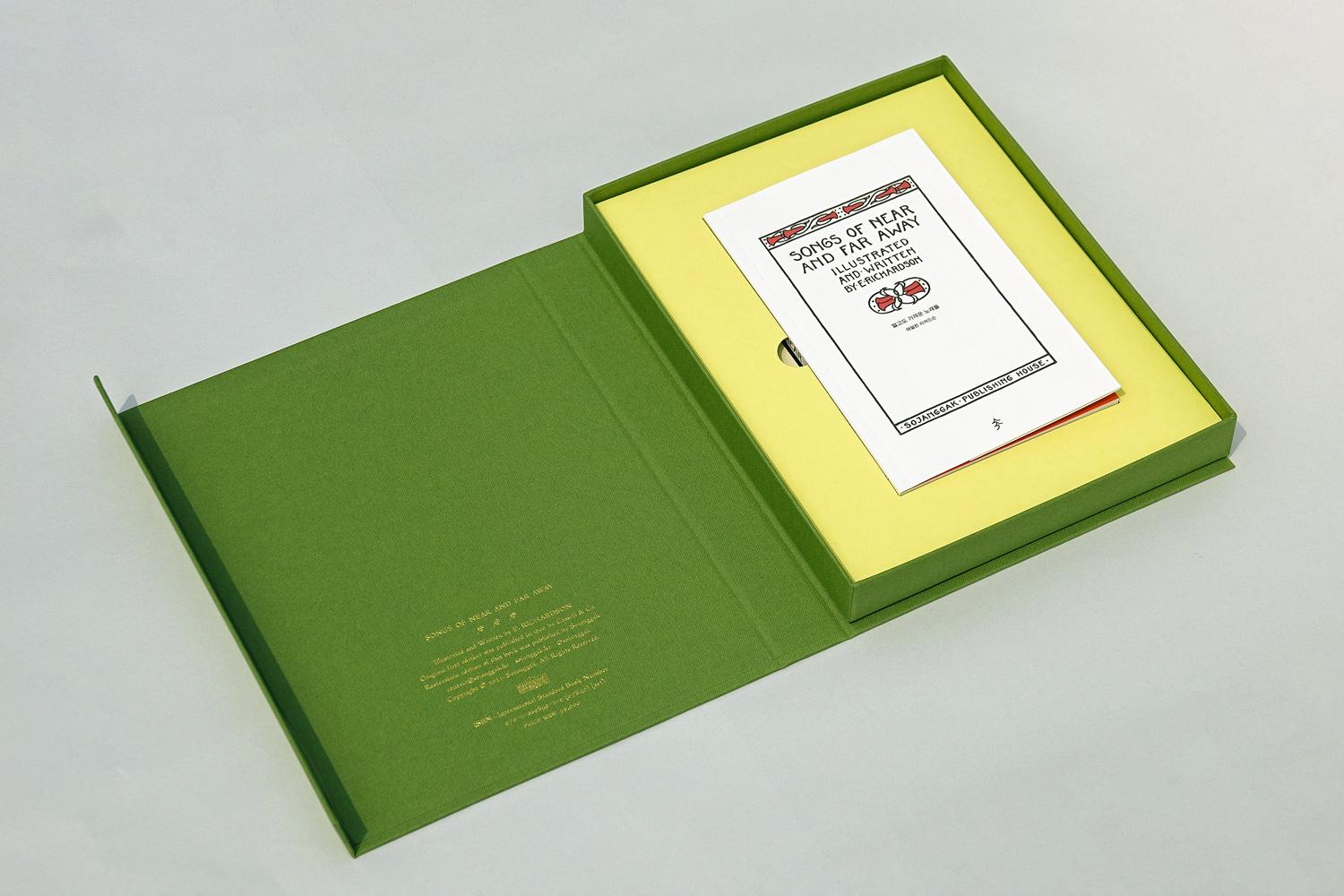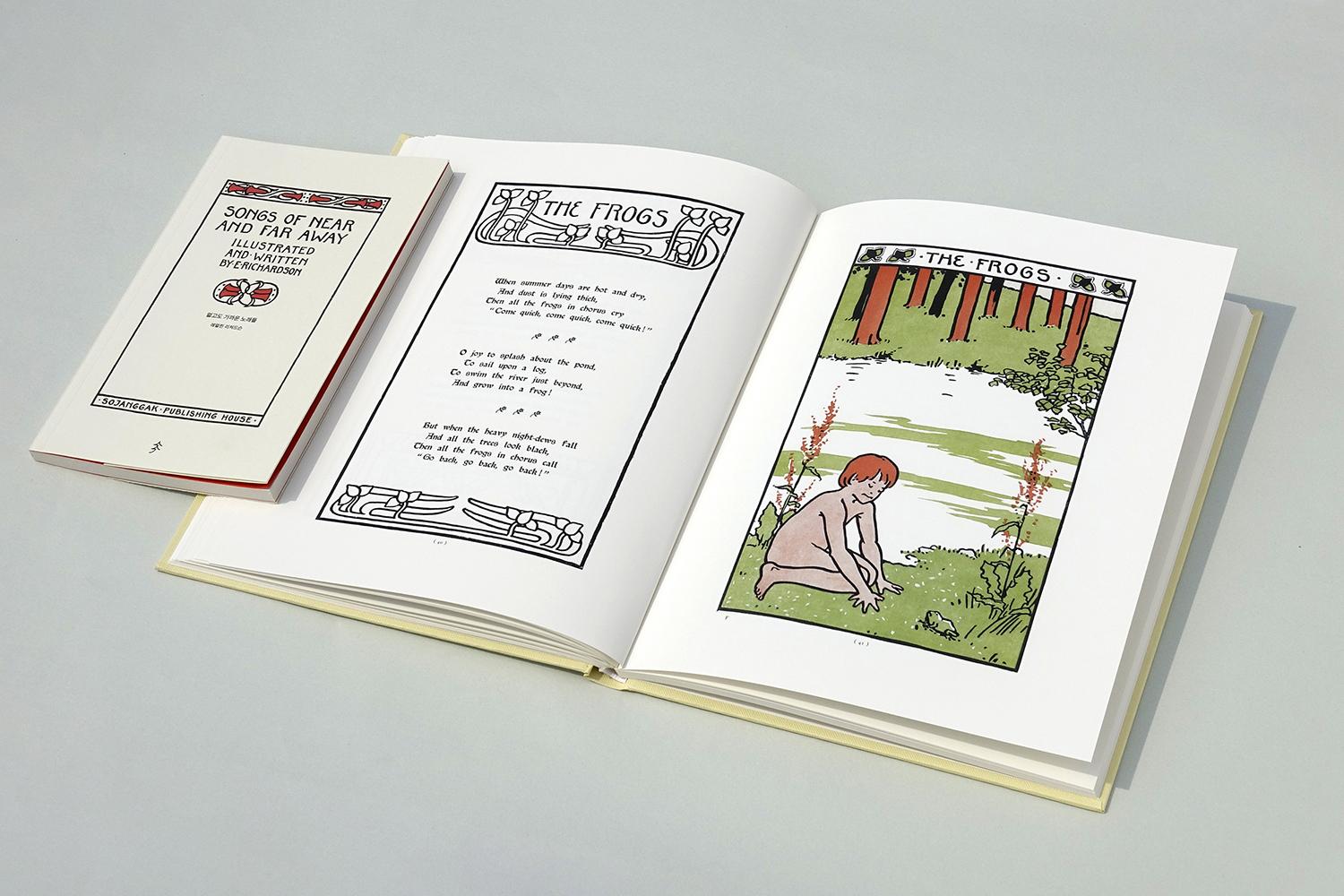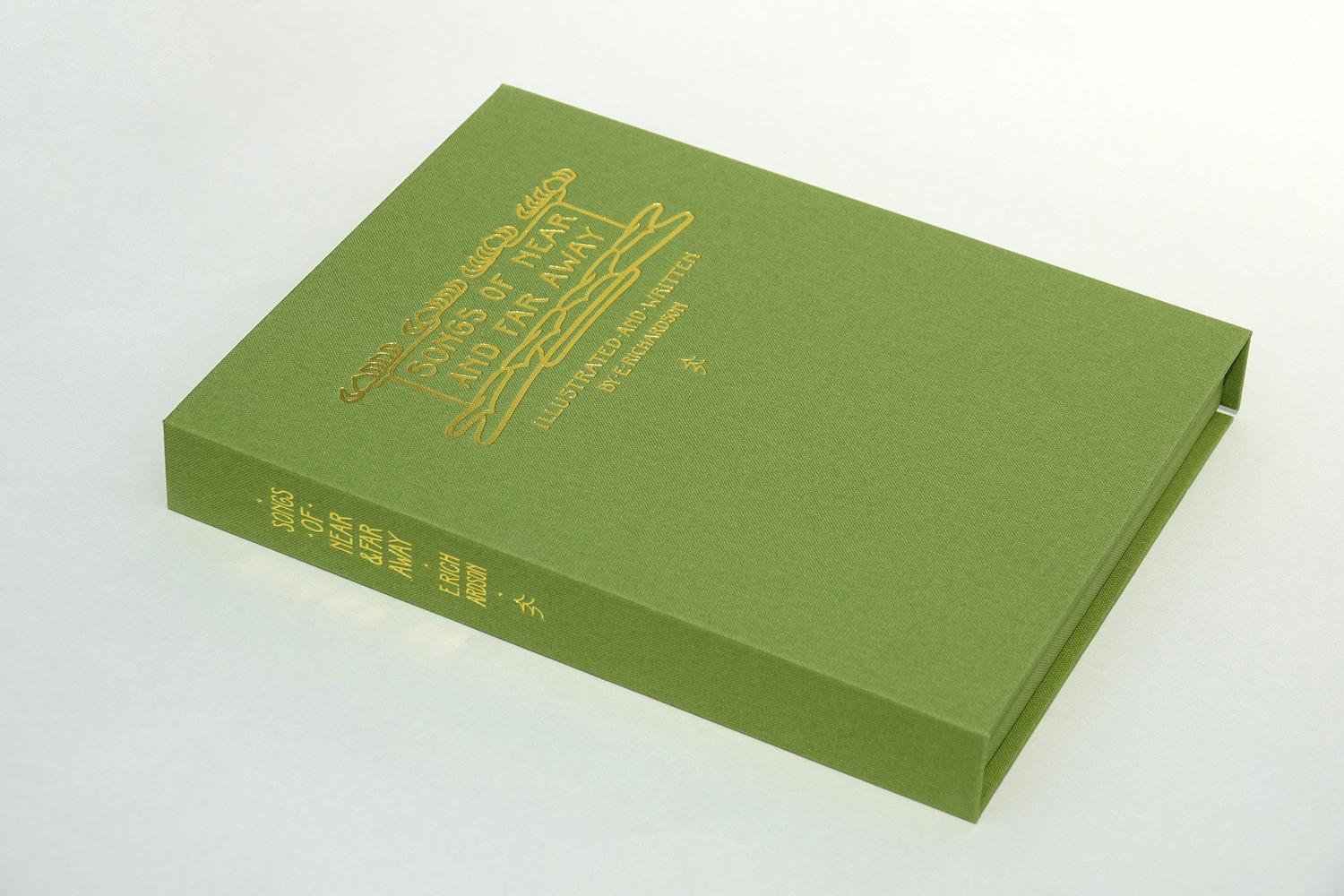
인터뷰: 소장각의 소장, 노성일 디자이너
소장각은 동남아시아를 중심으로
다양한 문화권의 이야기를 발굴해 그 가치와 매력을 독자에게 전합니다.
노성일 디자이너는 지역과 시대의 맥락을 존중하며,
현지인의 시선과 목소리를 온전히 담는 방식을 고집합니다.
캄보디아의 크메르 문자, 태국의 문방구, 미얀마의 달력까지,
동남아시아 곳곳의 이야기를 발견하고 다듬어 한 권의 아름다운 책으로 완성합니다.
책 속의 폰트 하나, 색감 하나까지도 맥락에 맞춰 치밀하게 선택하는
그의 집요하고 섬세한 디자인 방법론과 사용 폰트들을 살펴보세요.
Intro:
작은 책들의 집, 소장각
―독자분들을 위해 소장각의 간단한 소개를 부탁드립니다.
안녕하세요, 소장각의 노성일 소장입니다. 소장각은 ‘작은 책들의 집’이란 뜻의 출판사이자 디자인 스튜디오로, ‘주변부’, ‘독창성’, ‘아름다운 형태’ 세 가지 키워드를 중심에 두고 책을 만들어요. ‘주변부’라고 하면 흔히 원의 바깥을 떠올리시는데, 제가 말하는 건 그 개념보다는 바로 옆에 있는 친구나 이웃을 바라보는 시선, 그들의 이야기에 귀 기울이는 걸 말합니다. 사람들과 대화를 나누다 보면 눈이 반짝반짝 빛나는 순간들을 발견하게 되는데, 그게 바로 그 사람이 가진 독창성이라고 생각해요. 저는 그걸 건져 올려서 아름다운 형태로 엮는 일을 하고 있습니다.
―소장각이라는 이름은 어떻게 짓게 되셨나요?
‘규장각’에서 따와 ‘작은 책들의 집’이라는 의미로 지었습니다. ‘소장각'이라는 유행어를 의식해서 지은건 아니고요. 여기서 ‘작은 책’이란 유명하거나 주목받는 책이 아닌, 주목받지 않더라도 가치 있는 책을 말합니다. 또 이름에 한자*(小章閣)를 쓴 건, 아시아인으로서의 정체성을 생각할 때 한자 문화권의 역사와 의미가 중요하다고 느꼈기 때문이에요. 요즘은 한국에서 한자 쓰는게 많이 없어진 것 같고, 서양의 방식을 차용한 네이밍이 트렌드죠. 저는 그와는 다른 방향이 필요하다는 생각이 들었습니다.
*小[작을 소]‧章[글 장]‧閣[집 각]
집 모양의 한자 로고와 숲과 나무를 표현한 한글 로고
―한글 자소를 세로로 쌓은 형태의 로고, 한자로 구성된 로고도 매우 감각적인데요.
로고는 제가 직접 만들었고, 한자로 구성한 로고와 한글 자소 ‘ㅅ·ㅈ·ㄱ’ 으로 만든 로고 두 가지를 함께 쓰고 있어요. 한자가 *표의문자니까, 이미지처럼 보이길 바라는 마음에 집 모양으로 만들었습니다. 閣[집 각]의 문 아래 ‘各'이 사실 두 번 들어가 있는데, 손을 맞잡고 있는 두 사람처럼 보이지 않나요? 책은 여러 사람이 같이 공유하고 얘기를 나눌 때 더 풍성해진다는 의미를 담았습니다. 한글 로고는 책 등에 넣을 만한 작은 크기에서 보다 단순하고 선명한 로고가 필요하다고 생각해서 만들게 되었어요.
*표의문자: 하나하나의 글자가 언어의 음과 상관없이 일정한 뜻을 나타내는 문자. 고대의 회화 문자나 상형 문자가 발달한 것으로 한자가 대표적이다.
―'발굴'과 ‘덕질’이라는 키워드도 소개글에 자주 쓰시는데, 특별히 좋아하시는 이유가 있을까요?
저는 ‘발굴’과 ‘덕질’을 비슷한 개념으로 봅니다. 사람들이 눈을 반짝이며 이야기하는 건, 대개 오랫동안 관심을 가져왔고 계속 생각해 온 주제이거든요. 그건 그 사람의 ‘덕질’이고, 저는 그걸 찾아내는 ‘발굴’을 하는 거죠. 그 이야기들이 사소할 수도 있고, 상업적으로는 팔리기 어려울 수도 있어요. 하지만 저는 그 시간과 삶이 가진 가치를 디자이너의 시선으로 보고, 오랫동안 쌓인 것들을 아름답게 포장해 소개하는 게 중요하다고 생각합니다.
소장각의 책
⟪크메르 문자 기행⟫ 표지
―⟪크메르 문자 기행⟫은 대학원 논문으로 시작된 작업으로 알고 있는데요. 캄보디아 문자를 다루게 된 계기가 있었나요?
처음 시작은 예전부터 가고 싶었던 앙코르 와트를 보자는 마음으로 캄보디아로 떠난 거였는데요. 천 년 전의 고대 문자가 여전히 쓰이고 있고, 시간이 흐르며 전혀 다른 형태로 발전해 온 과정을 발견하게 되었어요. 그게 너무 흥미로워서 더 깊이 연구하고 싶다는 생각이 들었죠. 졸업 작품으로 책을 완성하기는 했지만 더 연구가 필요하다고 생각해서, 졸업 전시가 끝나자마자 바로 다음 주에 캄보디아로 가서 작업을 이어갔습니다.
크메르 문자의 계보와 해부도
―국내에서는 캄보디아 문화 관련 자료를 구하기가 쉽지 않았을 것 같아요. 현지에서 40여명의 전문가를 직접 만났다고 하셨는데, 그중에서도 기억에 남는 인물이 있나요?
제일 큰 도움을 줬던 분은 텝 소비챗(Tep Sovichet)이라는 분인데, 캄보디아의 유명한 젊은 디자이너에요. 선배 세대들이 해온 작업과 유산을 잘 물려받아서 정리하고, 그걸 현대 젊은 세대들이 쓸 수 있도록 생태계를 만드는 등, 다리 역할을 하고 있습니다.
제가 캄보디아 문자를 연구하는 과정에서 그의 도움을 많이 받았어요. 예를 들어, ‘타이포그래픽 아나토미(Typographic Anatomy)’이라고 해서 글자 구조와 각 부분의 명칭을 정리한 자료를 만들 때, 크메르 문자 버전은 정리된 자료가 없어서 태국 문자를 참고해서 작업하고 있었습니다. 텝이 보더니 원래 크메르 문자가 먼저 있었고, 태국 문자가 거기서 파생됐기 때문에 명칭도 서로 달라야 한다고 바로잡아 주었죠.
⟪크메르 문자 기행⟫ 대학원 졸업작품 버전의 모습
―대학원 졸업작품 버전과 최종 출판 버전이 다른 점이 있다면요?
물론 연구를 더 많이 해서 내용이 많이 달라졌는데요. 원래는 이렇게 본 책과 글자 보기집의 부록 부분을 분리해 S자 모양으로 구현하고 싶었습니다. 이걸 마지막에 못 살려서 조금 아쉽긴 해요.
⟪미얀마 8요일력⟫ 표지
―⟪미얀마 8요일력⟫은 ‘한국에서 가장 아름다운 책’에 선정될 만큼 만듦새와 공정에서 높은 평가를 받았는데요.
이 책은 아쉬울 것 없이 하고 싶은 걸 충분히 구현한 것 같아요. (웃음) 무려 9개 업체, 12가지 공정을 거쳐 완성되었습니다. 표지에는 인쇄 대신 금박과 먹박을 찍었어요. 미얀마의 파웅도우(Phaung Daw U) 사원이라는 곳을 가면, 사람들이 수백 년 동안 금박을 붙여 마치 눈사람처럼 형태가 변한 불상이 있는데요. 그 모습에서 착안해, 표지에도 숫자 08의 미얀마 숫자 표기로 눈사람 모양을 만들고 금박 모티프가 지나가는 형태로 만들었습니다.
표지 안쪽은 금색으로 실크 인쇄를 했는데요. 책이 달력에 대한 내용인 만큼 천문학을 많이 다루고 있어서 밤하늘의 별을 떠올릴 수 있는 패턴을 인쇄해 넣었습니다. 달력은 별을 보고 시간을 세는 학문이기에, 오랫동안 점성술과 천문학의 영향을 받아왔습니다. 또한 미얀마는 예로부터 ‘황금의 땅’이라 불려왔기에, 내지에 검정과 금별색만 사용하고 싶었어요.
금색이 돋보이는 ⟪미얀마 8요일력⟫ 내지
―이 책만의 특별한 디테일이 있다면 무엇인가요?
아무래도 미얀마가 생소한 지역이다 보니, 조금 더 쉽게 이야기를 전달하고자 이미지를 중심으로 전개되는 책을 기획했습니다. 그 과정에서 이해를 돕는 중요한 도판들은 본문에 붙여 넣었는데, 이는 판형 안에만 갇히는 책의 한계를 넘어 이미지를 확장해 감상할 수 있는 또 하나의 층위를 제공합니다. 책 전체에 걸쳐 8종의 부착면이 있으며, 모두 수작업으로 하나씩 붙였어요.
⟪미얀마 8요일력⟫의 확장되는 도판
―⟪미얀마 8요일력⟫의 금색, ⟪크메르 문자 기행⟫의 빨간색 등 책마다 색을 감각적으로 잘 쓰시는 것 같아요. 색을 선택할 때 어떤 경험에서 영감을 받으시나요?
태국은 제가 처음으로 혼자 여행했던 곳인데, 한국에서는 전혀 보지 못한 강렬한 색감이 인상 깊게 남았습니다. 한국과 적도 지역은 태양 빛을 받는 각도가 달라 색의 선명도가 다른데요. 한국은 여름을 제외하면 빛이 눕혀서 들어오기 때문에 톤 다운된 색이 많지만, 태국은 태양이 거의 수직으로 내리쬐어 그림자가 짙고 빛과 색이 훨씬 선명합니다. 그래서 동남아를 떠올리면 가장 먼저 ‘쨍한 컬러감’이 연상될 것이라 생각했고, 동남아시아 관련 책에서는 이런 강한 색 대비를 의도적으로 활용하고 있습니다.
특히 태국은 형광색을 일상적으로 많이 사용합니다. 택시나 각종 공산품에서도 쉽게 볼 수 있죠. 그래서 ⟪태국 문방구⟫ 표지와 내지에 형광 초록을 사용하면 태국을 다녀온 사람들에게 더 강하게 각인될 것이라 생각했습니다.
⟪태국 문방구⟫
―⟪태국 문방구⟫의 표지에는 영어, 한국어, 태국어가 함께 쓰였는데요. 서로 다른 문자가 조화를 이루도록 폰트를 고르신 기준이 궁금합니다.
이 표지를 만들 때는, 책에 나오는 태국의 문구 패키지처럼 빈티지한 인상을 주고 싶었어요. 이런 패키지들은 처음 제작 당시 컴퓨터 대신 손으로 제도하여 작업했을 것이기에, 그 분위기를 표지 디자인에도 구현하고자 했습니다. 색을 깔고 면과 선만으로 구성하는 방식을 택했고, 태국어 폰트는 각도기로 제도한 듯 투박한 디테일이 살아있는 것을 골랐습니다. 한글 폰트도 비슷하게 모서리가 작도된 티랩의 「CDR 제스트」를 사용했죠. 매끈하고 세련된 느낌보다는 손으로 작업한 듯한 느낌을 살리고 싶었어요.
―매번 다루시는 주제가 굉장히 구체적이고, 그에 꼭 맞는 필자를 섭외하시는 점이 인상 깊었어요. 원고가 먼저 있고 제안을 받으시는 건가요, 아니면 주제를 정한 뒤 필자를 찾으시나요?
대부분 사람들을 만나서 그들의 덕질을 듣고 주제를 길어올립니다. 동남아 책을 계속 내다 보니 관련 콘텐츠를 찾으려고 인스타그램이나 블로그를 많이 살펴보곤 하는데요. ⟪태국 문방구⟫의 경우도 태국에 이주해 현지 문방구에 대해 꾸준히 기록하는 작가님의 SNS를 보고 제안했는데, 마침 그 당시 소장각 이름으로는 한 권밖에 나오지 않았던 ⟪크메르 문자 기행⟫을 이미 알고 계셨고, 동남아시아를 바라보는 시선에 공감해 주셔서 함께 책을 만들게 되었습니다.
―요즘은 직접 책을 쓰시기보단 다른 분들의 콘텐츠를 기반으로 엮거나 번역하는 책이 많아진 것 같아요. 둘 중 선호하시는 방식이 있나요?
책을 직접 쓰는 경우에는 자료를 깊이 파고들며 내용을 알아가는 즐거움이 크고, 글쓰기를 통해 스스로를 돌아보는 과정에서 성취감을 느낍니다. 흩어진 정보를 하나의 실로 꿰면서 메시지를 찾아가는 과정이 특히 재미있고, 그 메시지가 다음 단계의 저를 만들어가는 계기가 되기도 해요. 반면 다른 필자와 작업하면, 제가 할 수 없는 이야기를 다른 시선과 방법으로 풀어낼 수 있다는 점이 매력적이어서 일부러 다양한 분들을 초대해 책을 만듭니다. 같은 주제여도 다른 작가의 목소리가 모이면 소장각의 이미지를 함께 만드는 셈이고, 그렇게 이 브랜드 안에서 저 뿐만 아니라 여러 사람이 함께 생태계를 형성할 수 있다고 생각해요.
in sight of TASTE!
SPEEDY 10문 10답
Q1. 유독 좋아하는 후가공은?
박(음각과 양각… 박으로 레이어 짜기 등)
Q2. 본능적으로 손이 가는 색 조합은?
보색 대비, 그리고 쨍한 색깔
Q3. 내 사진첩에서 가장 많은 비율을 차지하는 이미지는?
동남아 여행중 찍은 종교적인 모티프
Q4. 최애 애니메이션과 웹툰을 추천한다면?
진격의 거인, 레사, 마법스크롤 상인 지오, 잔불의 기사
Q5. 작업할 때 무한반복 하는 노동요는?
심장을 두근거리게 하는… K-POP (원픽: aespa-Armageddon)
Q6. 동남아 커피 vs 차 vs 디저트
디저트 (망고 스티키 라이스!)
Q7. 언젠가 꼭 가보고 싶은 여행지는?
남아메리카
Q8. 작업할 때 가장 많이 떠올리는 한 문장(혹은 좌우명)은?
그래도 해야지 어떡해
Q9. 완전히 떠나보낸 취향은?
미니멀리즘
Q10. 나에게 자극을 주는 디자이너가 있다면?
대만의 왕쯔홍(Wang Zhihong) 디자이너